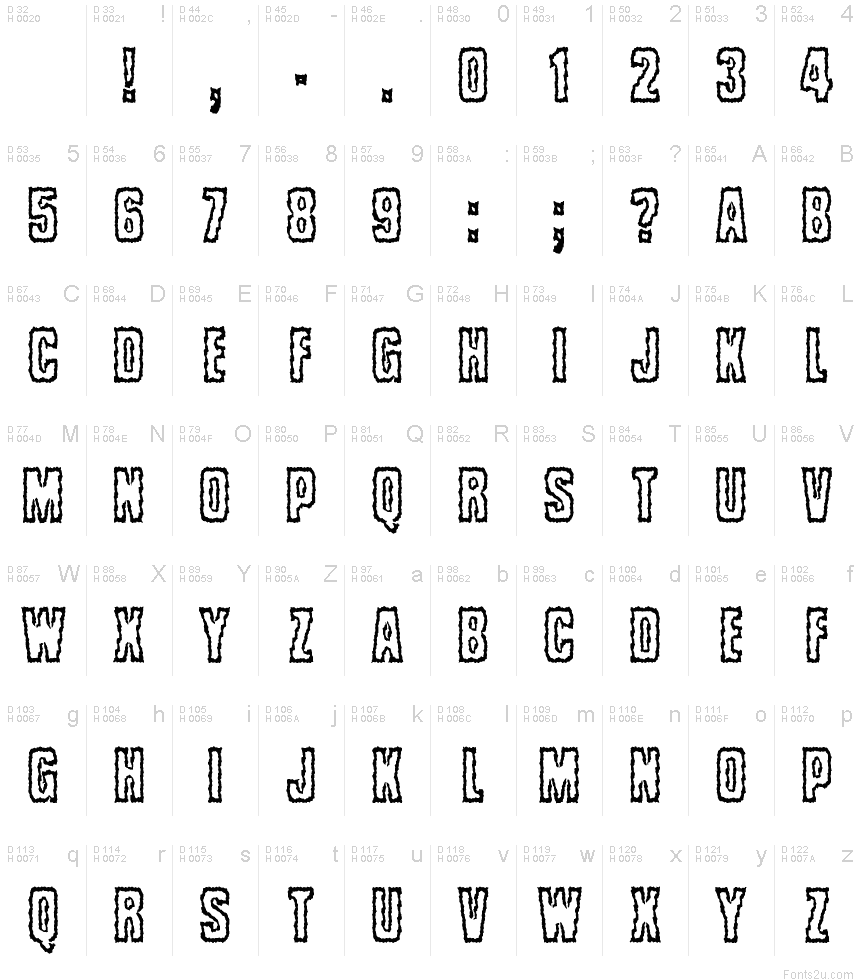
خط Brrritty من Pit D Gulash هو خط عرض مجاني ذو حواف متآكلة ومفرغة، يبدو وكأنه نُحت من صخرة أو سال من مادة لزجة. كل حرف عبارة عن كتلة ضخمة وعمودية ذات حواف مهتزة وممزقة، مما يضفي على النص طابعاً خشناً وجريئاً. وبفضل الفراغات الداخلية، يظل الخط خفيفاً بشكل مدهش، مما يجعل العناوين الكبيرة تبدو صاخبة وقوية دون أن تتحول إلى كتل سوداء ثقيلة على الصفحة أو الشاشة.
باستخدام Brrritty، ستضفي لمسة فورية من التميز على ملصقات الرعب، ومنشورات الهالوين، ومجلات DIY، وتصاميم حفلات البانك أو الميتال، وأغلفة المنتجات ذات الطابع اللزج، وصور YouTube المصغرة الجذابة. يخلق الخط الخارجي غير المنتظم تأثيراً مرسوماً يدوياً بحواف تكاد تكون مهتزة، مما يجذب الانتباه من بعيد. يعمل هذا الخط المجاني بشكل أفضل عند استخدامه بأحجام كبيرة، ويتماشى جيداً مع خط بسيط ومحايد (sans serif) للنصوص الأساسية للحفاظ على توازن التصميم.